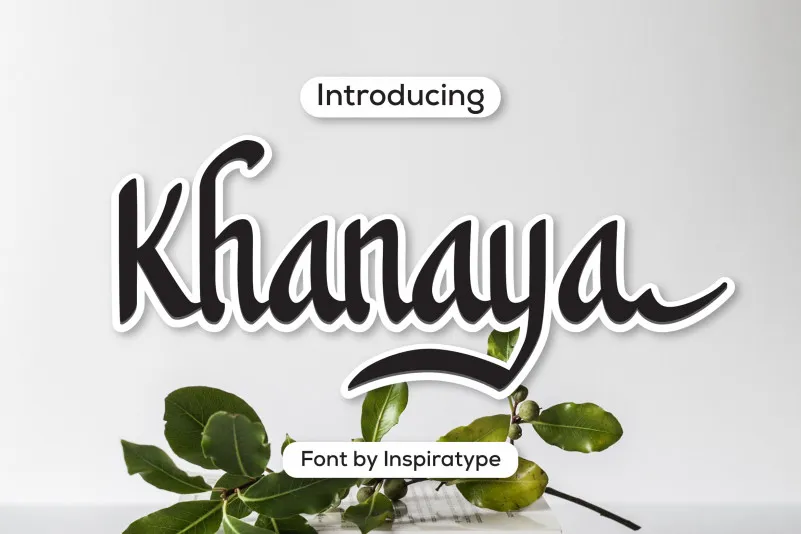
Khanaya Font
A “Khanaya Font” é uma tipografia serif que evoca as posters clássicos. Inspirada pelo design elegante e sofisticado dos anúncios antigos, esta fonte transmite um toque de autoridade e requinte ao texto que usa. Seja para cabeçalhos profissionais ou textos mais discretos, ela oferece um formato agradável e coerente com qualquer tipo de layout. A “Khanaya Font” é perfeita para manusear em projetos gráficos onde uma fonte elegante pode fazer toda a diferença, seja para anúncios impressos, logotipos ou até mesmo design editorial.
Designer: inspirasign